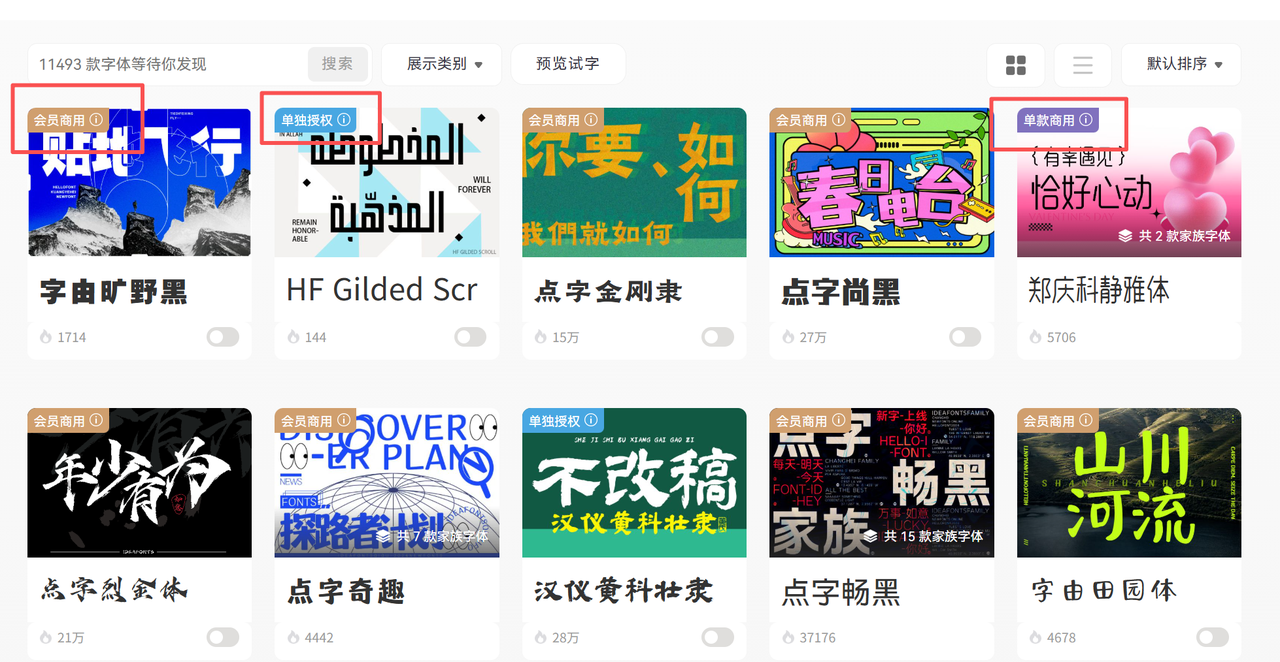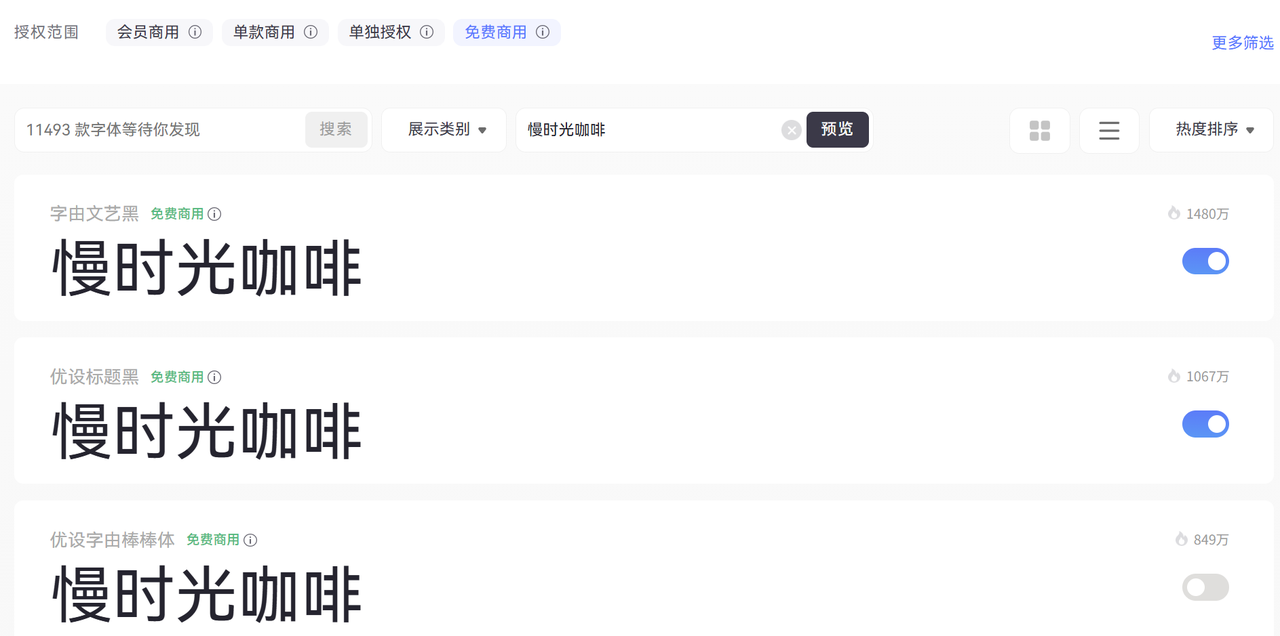
免费无版权字体去哪找?我常用的6个宝藏网站分享
字由是我电脑里必装的工具。它不只是一个字体网站,更像是一个专业的字体管理软件。
我最喜欢它的几个地方:
一键激活,随用随开
不需要把字体文件下载到系统字体库里。在字由里激活某款字体后,打开PS、AI、Figma这些软件就能直接用,这样我的字体库始终很干净,不会因为装了几百款字体导致电脑卡顿。
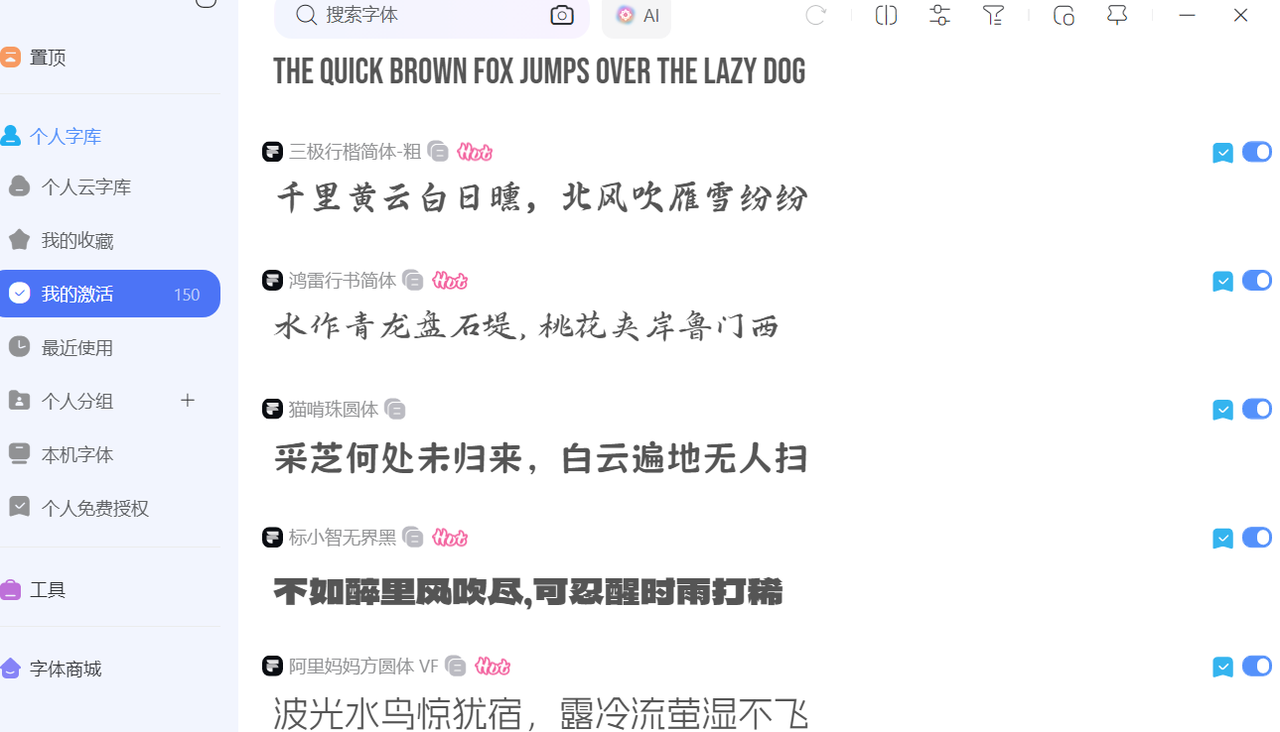
商用授权标注清晰
每款字体都明确标注了是"免费商用"还是"授权使用"。我现在接项目前,都会先在字由里筛选"免费商用"这个标签,完全不用担心版权问题。
字体预览实时显示
可以直接输入我的文案内容,实时预览不同字体的效果。比如我要做一个咖啡店的Logo,就输入"慢时光咖啡",然后切换字体对比,很快就能找到最合适的那款。
字由收录了上千款字体,包括思源黑体、阿里巴巴普惠体、站酷系列等热门免费字体。对于经常需要切换字体的设计师来说,这个工具能节省大量时间。
Google Fonts
我常用的几款:
- Noto Sans SC(思源黑体):Google 和 Adobe 合作开发的,中文显示效果特别好,我做APP界面时经常用
- Roboto:英文界面的万能字体,简洁现代
- Noto Serif SC:宋体风格,适合长文阅读
网站支持按语言、字重、倾斜度筛选,还能直接测试字体效果。唯一的小问题是中文字体数量不如国内平台多。
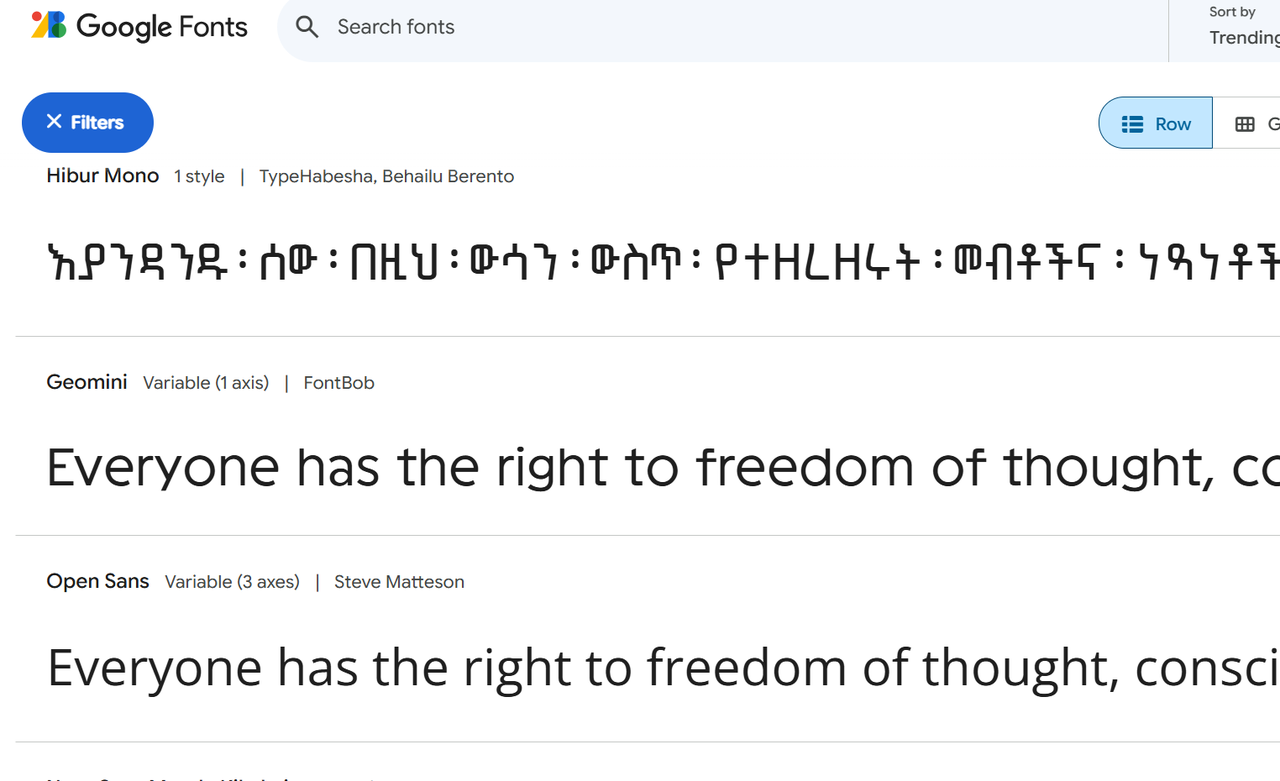
猫啃网
这是一个纯粹的免费字体分享社区,站长持续更新各种免费商用字体。我经常在这里发现一些小众但很有特色的字体。网站会标注每款字体的授权范围,有的可以商用,有的只能个人使用。下载前一定要看清楚说明。
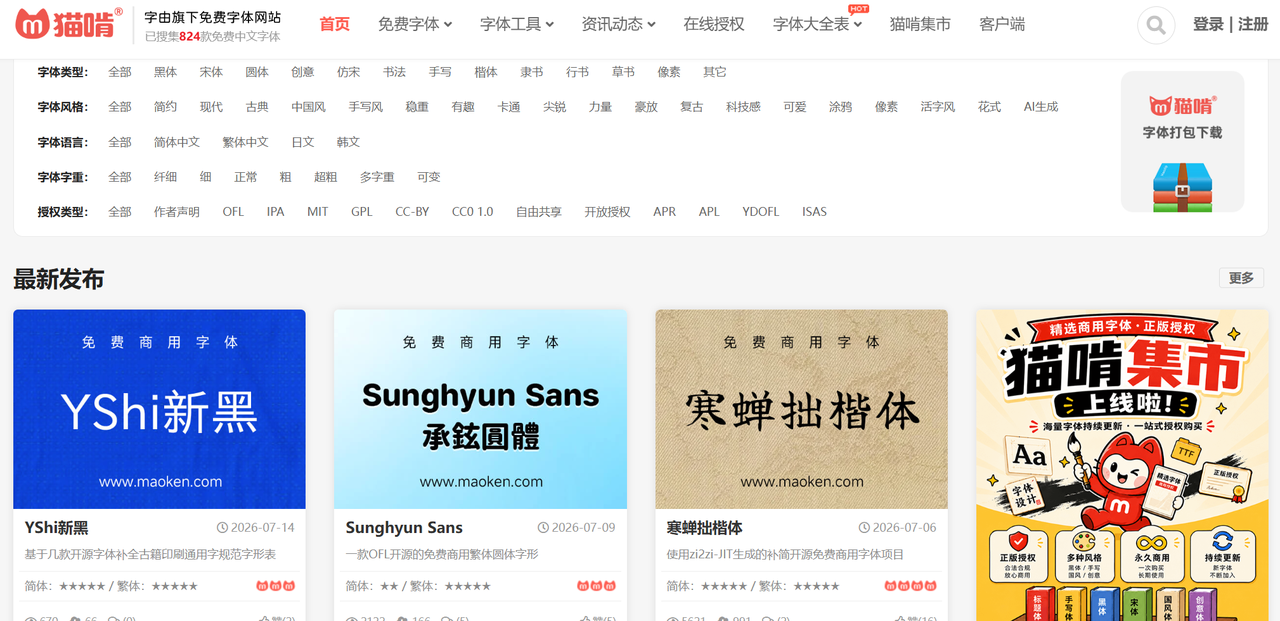
100font
这个网站只收录完全免费商用的字体,不用担心误下载到有版权限制的。
界面非常简洁,没有广告,下载速度也快。我手机上也收藏了这个网站,有时候在外面临时需要找字体,用手机就能搞定。
收录的字体包括:
- 阿里巴巴普惠体
- 优设标题黑
- 站酷快乐体
- 庞门正道系列
每款字体都有详细的预览图和授权说明文档,非常贴心。
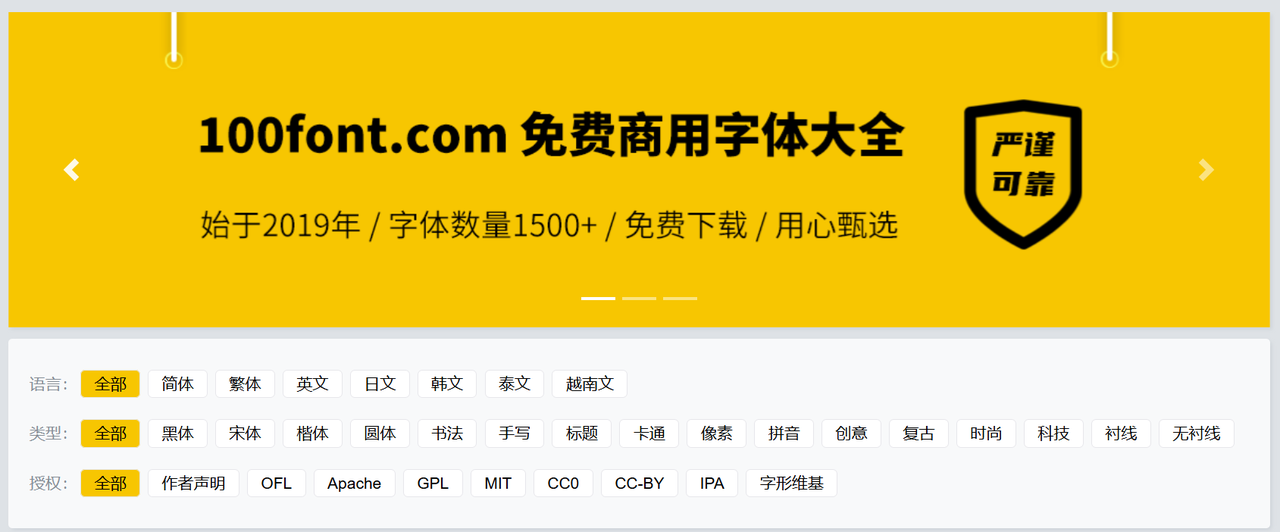
字体天下
这是我最早接触的字体网站之一,内容很丰富,但需要注意的是,不是所有字体都免费商用。
我的使用方法:
- 在搜索框输入"免费商用"
- 或者点击"免费字体"分类
- 下载前仔细看字体详情页的授权说明
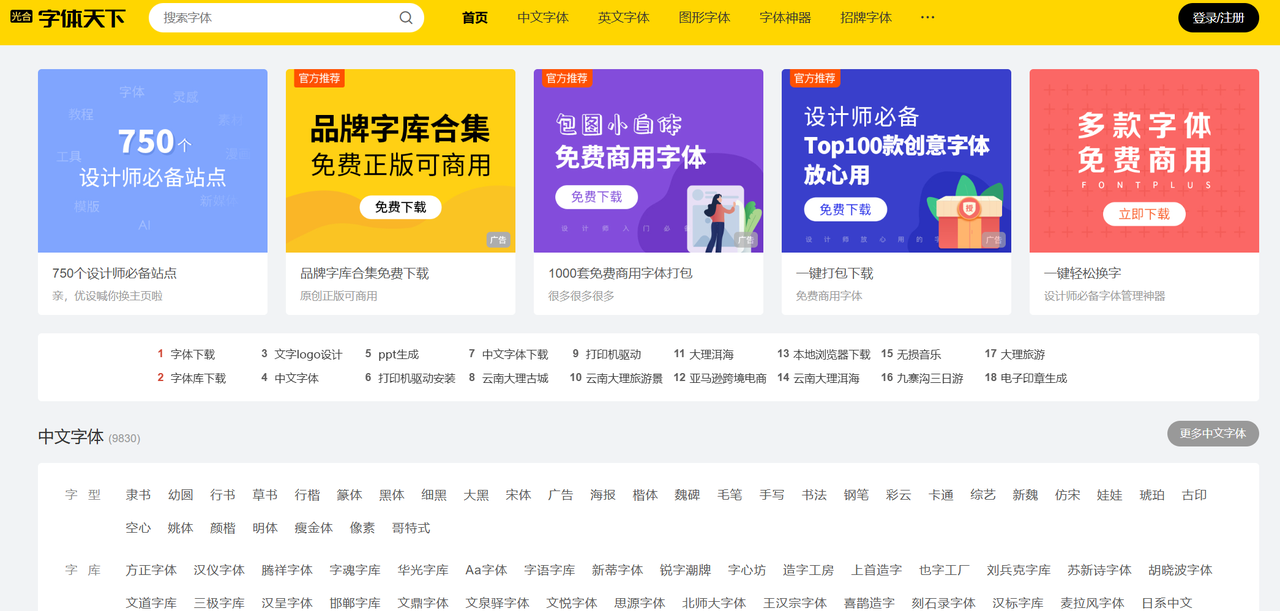
自由字体
站长会定期整理最新的免费商用字体,并附上官方授权链接。
我觉得这个网站最负责任的地方是,它不仅提供下载,还会把字体的官方授权文件链接贴出来。如果客户对字体版权有疑问,我可以直接把官方授权文件发给他们。
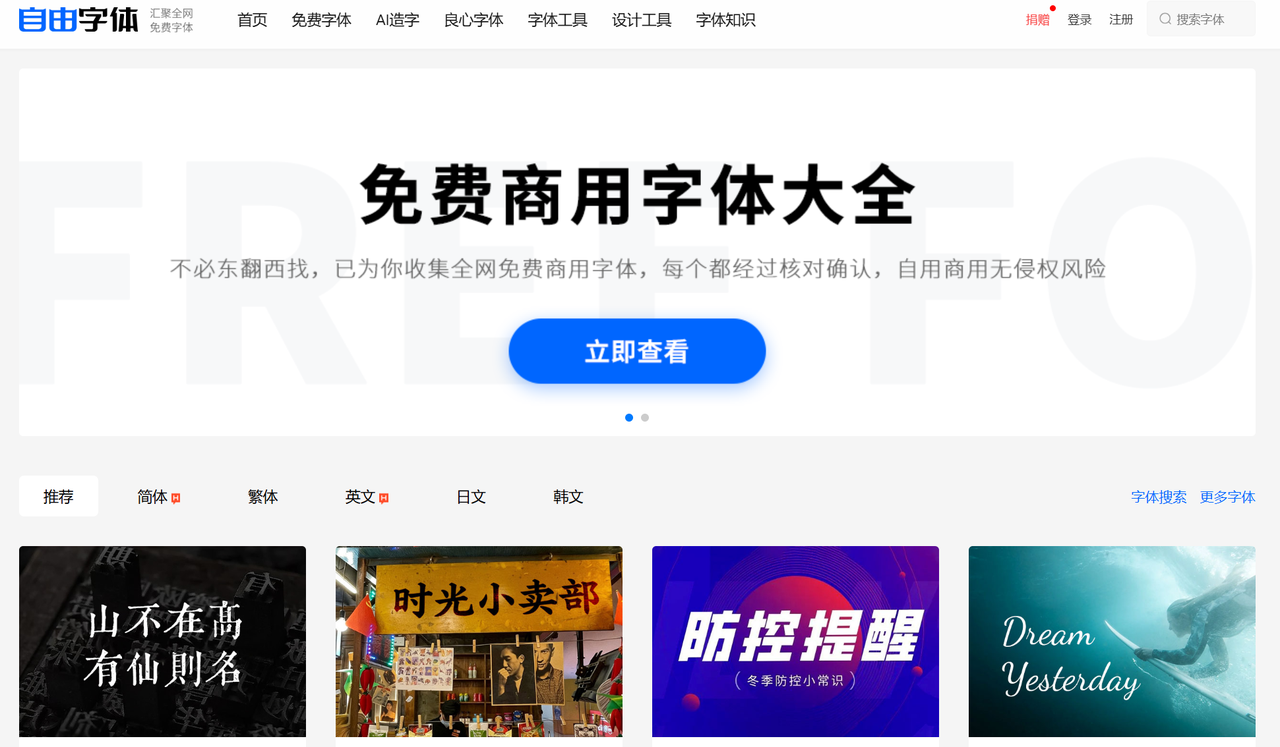
我现在的工作流程是:新项目开始前,先在字由里激活几款候选字体。